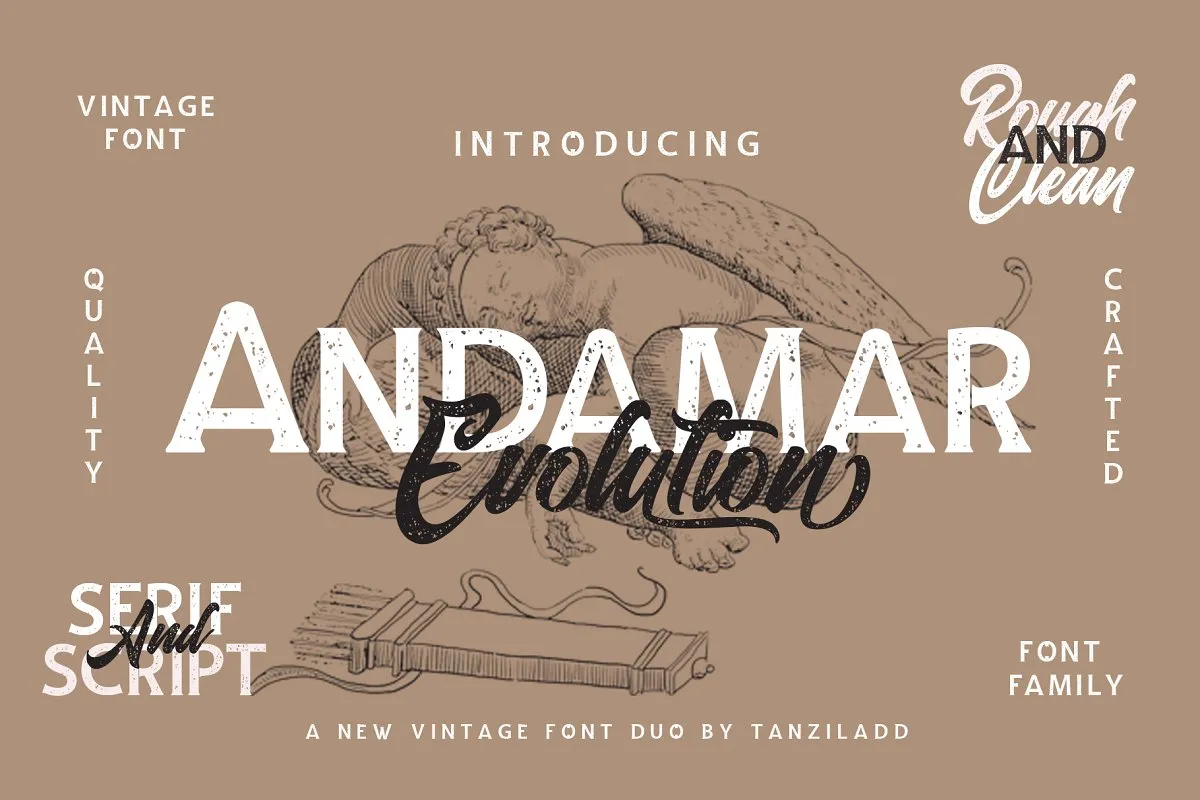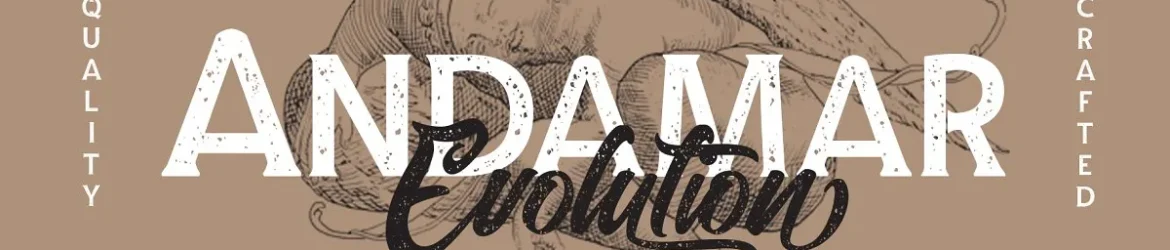
Andamar Font Family é uma família de tipos para rótulos que surgiu do desejo de criar algo elegante e atemporal. Este tipo foi desenvolvido por Tanziladd, um designer com experiência suficiente para capturar os detalhes necessários. Andamar tem a propriedade premium de ser vendida na CreativeMarket, mas estamos felizes em oferecê-la gratuitamente agora enquanto ainda está disponível. O design desta família de tipos é focado no lado visual e nas nuances que podem tornar uma etiqueta única e chamativa. O designer Tanziladd encontrou um equilíbrio entre a curvatura suave e as formas grossas, resultando em um tipo vintage com legibilidade alta. Este tipo parece ter um certo charme familiar e pode ser facilmente reconhecido, mas ao mesmo tempo é moderno e não apela à nostalgia exagerada. Ao trabalhar com Andamar Font Family, você tem a oportunidade de criar rótulos que combinam elegância, conforto visual e legibilidade. É perfeito para aquelas marcas que buscam um tipo versátil capaz de se adaptar ao tempo e às tendências sem perder seu tom tradicional ou vintage.